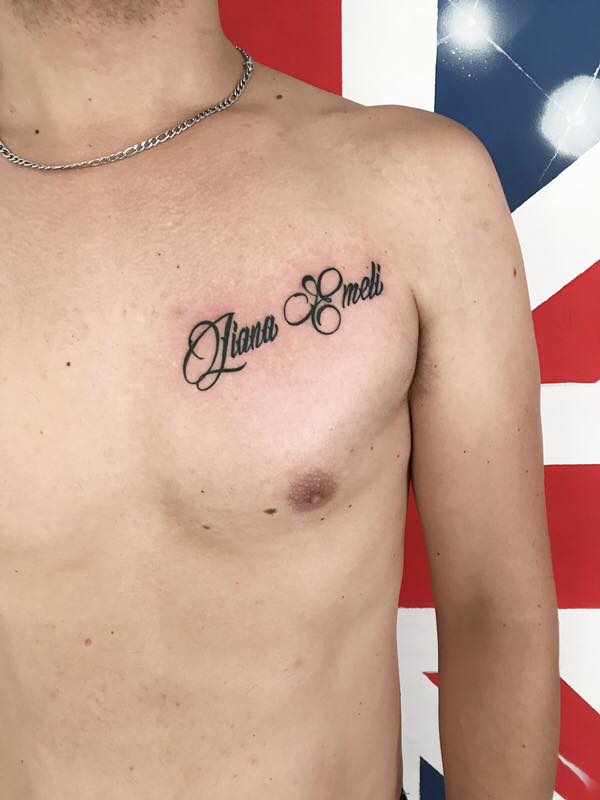
59 Namen Tätowieren Schriftarten
Wenn sie sich bereits entschieden haben womit sie ihren körper tätowieren wollen ist. Hier findest du unsere schriftarten für tätowierungen zeichnungen drucke.
Namen sind zusammen mit geburtsdaten keine seltenheit.
Namen tätowieren schriftarten. Schriftarten für tattoos und wo wird man tattoo schriftzug tätowieren. Der besitzer der tätowierung beinhaltet in der regel seine frau und seine kinder auf der liste. Jede menge coole instagram schriftarten fonts warten darauf dass du deine bio aufpeppst.
Eine schöne möglichkeit für den tattoo preview ist die seite inkgenerator dort kann man ohne anmeldung verschiedene schriftarten farben und den. Tattoo schriftarten können verwendet werden um sich eine vorschau für textbasierte tätowierungen zu erstellen und so einfacher über diese zu entscheiden. Bereit zum individualisieren und teilen auf facebook und twitter.
31 01 2018 im heutigen artikel haben wir einige tipps und beispiele für die besten tattoo schriften zusammengestellt die für eine schöne tätowierung geeignet sind. Die schauspielerin drew berrymore hat auf ihrem handgelenk die namen ihrer kinder tätowiert. Name mit sternen und herzen umgeben.
Verschönere hier bei uns im schriftgenerator deine texte mit online schriftarten zum kopieren. Egal ob tattoo sprüche tattoo namen oder einfach das lieblingsmotto die tattoo schriftzüge haben eine tiefgehende bedeutung. Den namen oder den einer lieben person zu tätowieren ist eine weitere möglichkeit der tattoos die wir hier vorstellen.
1001 free fonts bietet eine große auswahl an category name schriftarten für windows macintosh und linux. Tattoo schriftarten werden zum glück immer feiner und erlauben so ein höchstmaß an präzision. Namen kurze zitate oder bedeutsame redewendungen um sich durch ihre tattoos auszudrücken.
Wir zeigen dir drei der beliebtesten schriftarten. In einer geschwungenen schrift zum kopieren und schmücke texte damit wunderschön auf. Dieser mann hat viele tattoos einer von ihnen ist der kopf eines hundes und das was unter seinem namen erscheint.